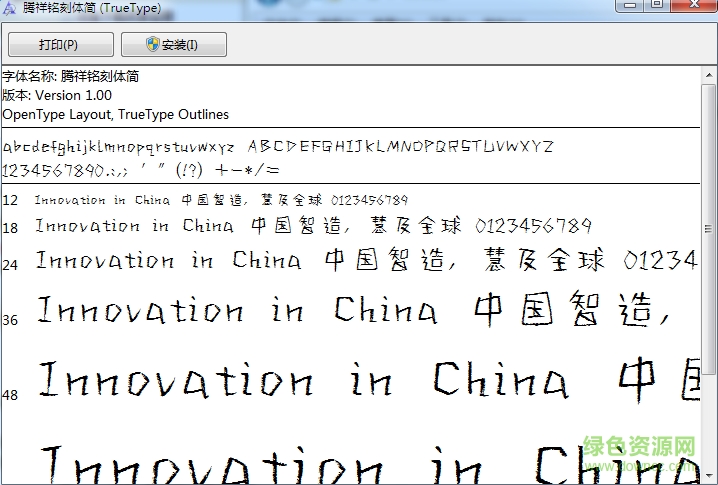
騰祥銘刻體簡是一款非常有特色的電腦字體,字形大小有別;筆畫粗細有致,看似不經意卻實則有意而為之,在經意與不經意間尋求平衡,浸透設計師書寫功力。本作品可適用于包裝設計、廣告設計、網頁設計等。有需要就來綠色資源網下載!
騰祥銘刻體簡由設計師孔淼先生書寫設計,風格鮮明、特點突出。筆畫古樸雅拙、精雕細刻。筆畫猶如用刀在石壁上一筆筆刻畫出的圖案。筆筆勁力、力透紙背、飛白顯露,彰顯刀刻之功。